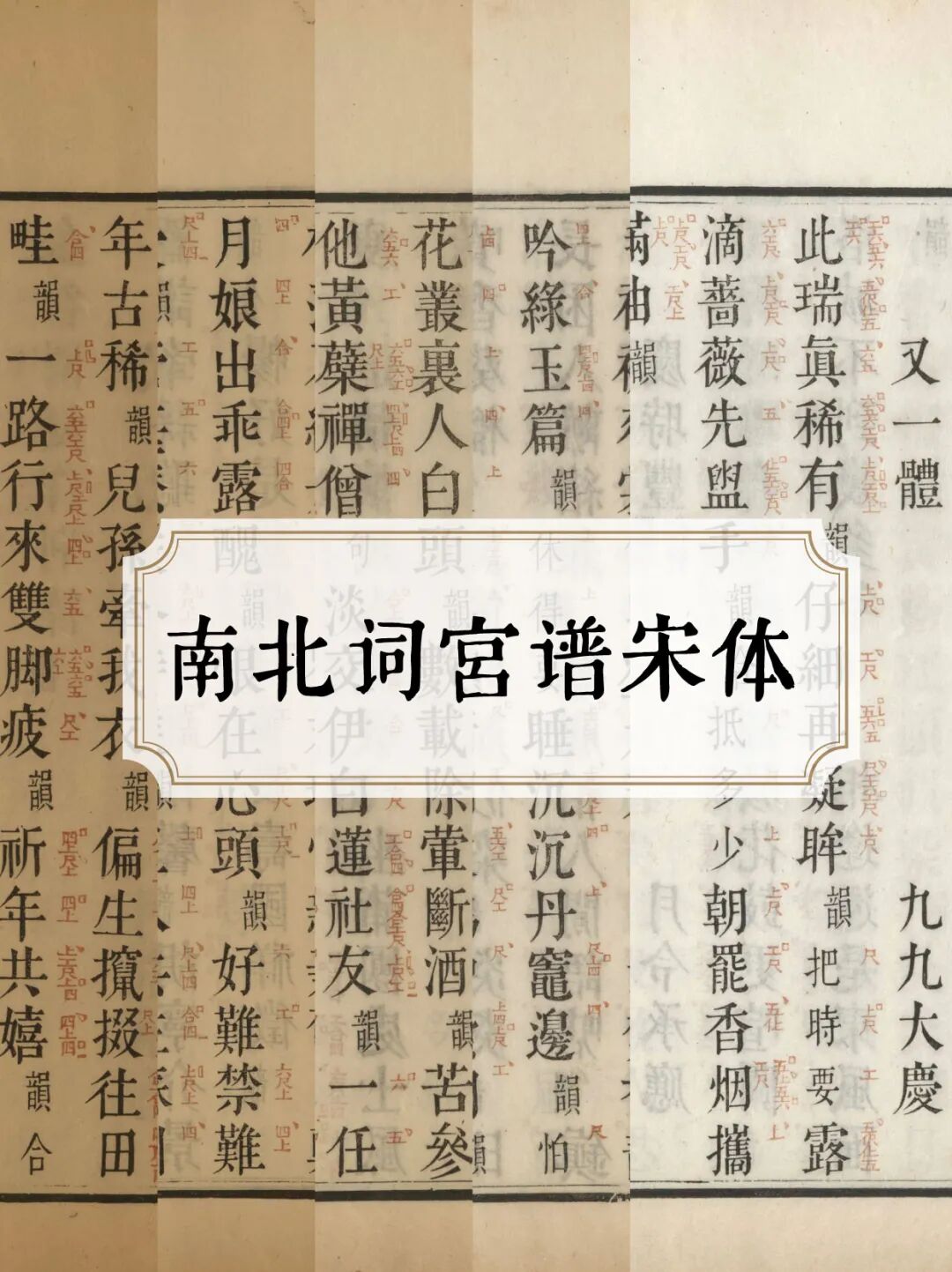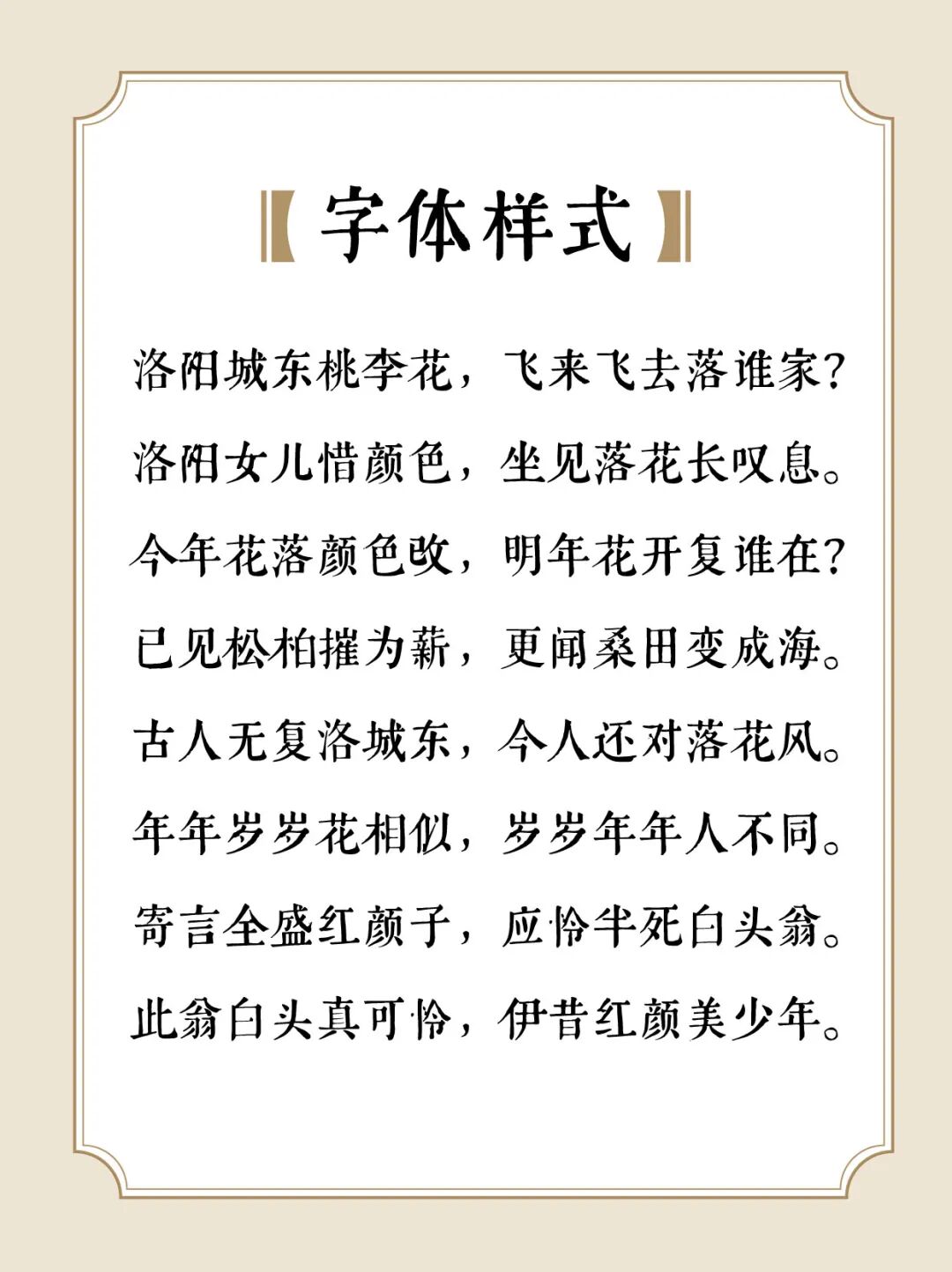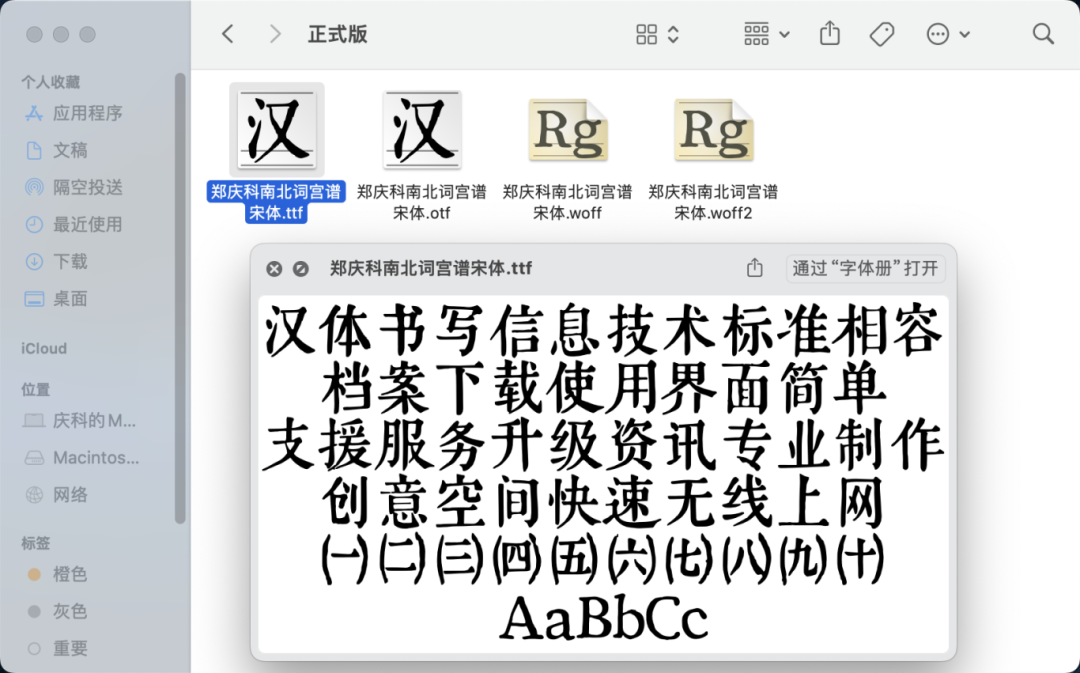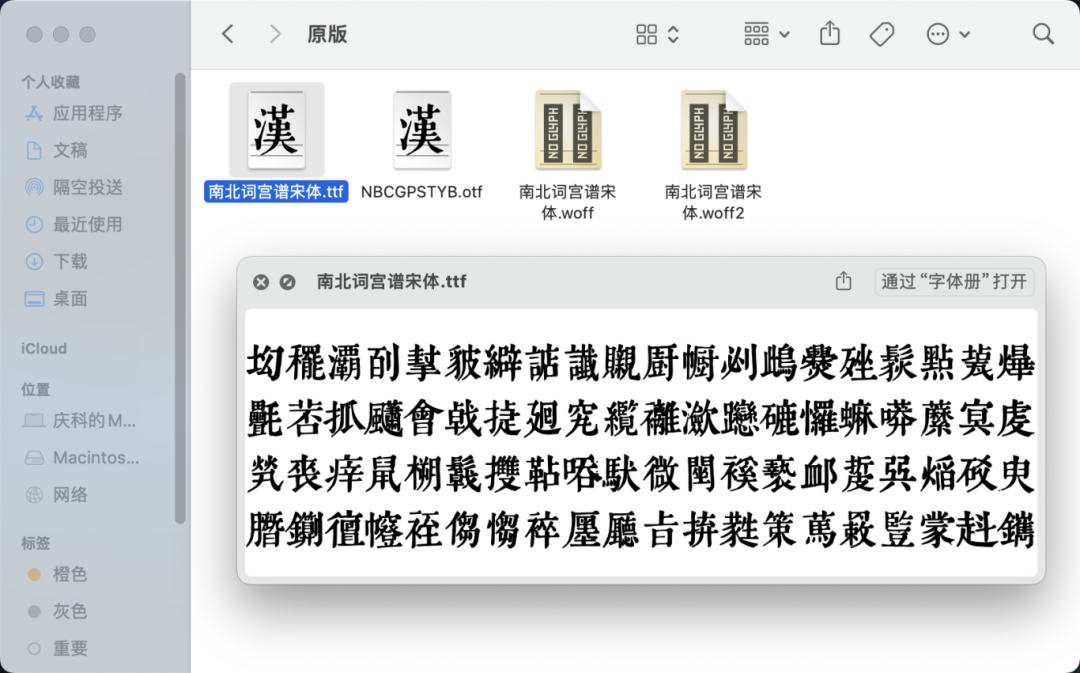
庆科字库发布新免费商用字体南北词宫谱朱体
人工智能正在逐步将各个行业重塑,尤其是与本人职业相关的插画、设计、摄影等行业在第一波就受到了巨大冲击
与其等着被拍死,倒不如主动出击,于是我尝试用人工智能的方式生产字体库。
方法很简单——组装一台游戏电脑,使用生成对抗网络(GAN),进行多次训练生成即可
复刻字体,原字型取自《新定九宫大成南北词宫谱》,字型线条未优化,保持原样未动。原因一:保持原版古朴质感的风格;原因二:验证新技术的可行性。
从古籍中拆分出30余万个字符图像,人工筛选出5000余个字符图像,然后将图像输入本地部署的模型进行对抗训练,最终输出为一个令人基本满意的字库文件。
本项目AI用时约10h,前期筛选与后期修复用时约7天,极大地减少了人工操作时间并减轻了劳动强度。
本字体支持国家标准GB 2312编码字符集、大五码字符集、Unicode基本字符集,包含中文简体、中文繁体、拉丁字母、阿拉伯数字和各类标点共计21943个字符。
本字体有2个版本,其中一款为原版复刻,仅包含人工筛选出的5716个字符(繁体+简体)。